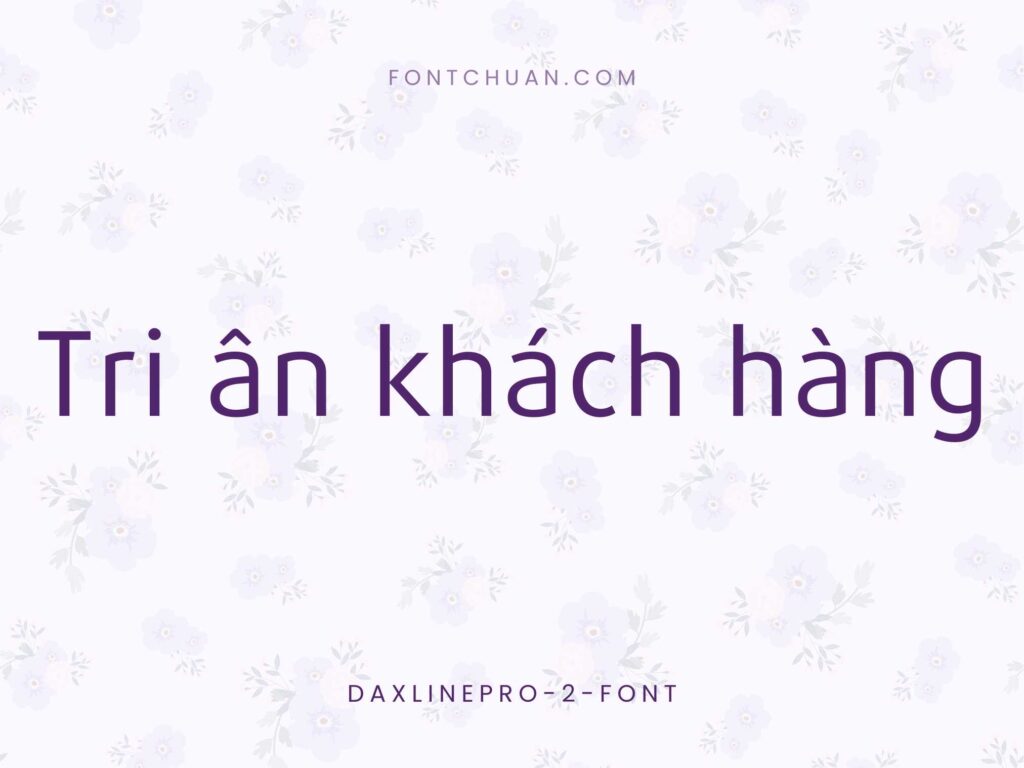
Font FS Daxline Pro Trọn Bộ Việt Hóa
Daxline Pro là một họ font sans-serif hiện đại, được thiết kế bởi Hans Reichel và phát hành bởi FSI Fonts und Software GmbH vào năm 2006. Font này nổi bật với các đường nét sạch sẽ, cấu trúc hình học và độ tương phản thấp, mang lại cảm giác chuyên nghiệp và dễ đọc. Với sự Việt hóa của Phông Chữ Việt, Daxline Pro hỗ trợ đầy đủ các ký tự tiếng Việt, giúp người dùng dễ dàng áp dụng trong các thiết kế đa ngôn ngữ. Thành viên của Font Chuẩn đã sưu tầm và chia sẻ font này nhằm đáp ứng nhu cầu của cộng đồng thiết kế.
Về đặc điểm thiết kế, Daxline Pro bao gồm 5 kiểu chữ khác nhau: Regular, Light, Medium, Bold và ExtraBold, mang lại sự linh hoạt cho các dự án thiết kế. Font này hỗ trợ đa ngôn ngữ, bao gồm các ngôn ngữ như Anh, Pháp, Đức, Ý, Tây Ban Nha và nhiều ngôn ngữ khác. Daxline Pro đặc biệt phù hợp cho các ứng dụng như thiết kế logo, tiêu đề, văn bản trên web, in ấn và các ấn phẩm quảng cáo. Ngoài ra, font này cũng thích hợp cho các sự kiện như lễ hội, sinh nhật, Valentine và Trung thu, mang lại cảm giác hiện đại và tinh tế. Trong lĩnh vực ngành nghề, Daxline Pro được ứng dụng rộng rãi trong quảng cáo, thiết kế thiệp cưới, giáo dục và công nghệ, góp phần tạo nên sự độc đáo và thu hút cho các sản phẩm và thương hiệu.